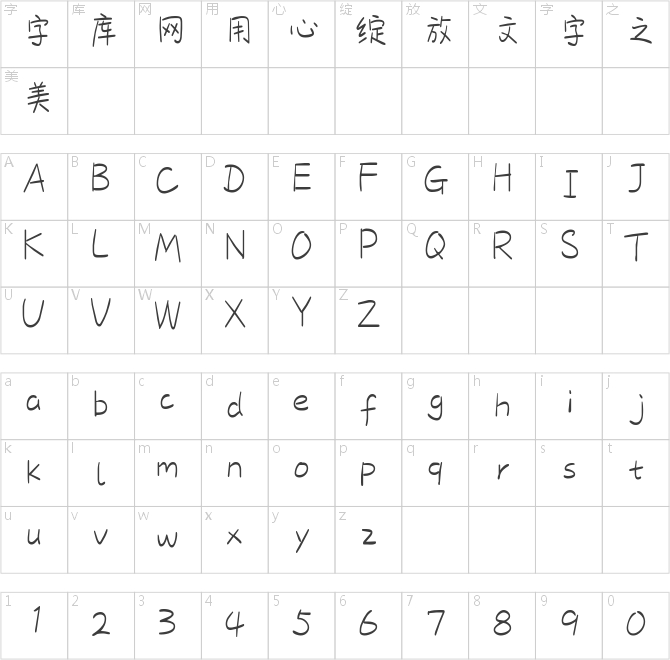
你與溫柔皆可珍藏字體下載文道你與溫柔皆可珍藏
你與溫柔皆可珍藏字體文道你與溫柔皆可珍藏字庫(kù)是一款讓人賞心悅目、百看不厭的中文字體,適合各類(lèi)廣告和產(chǎn)品包裝設(shè)計(jì)應(yīng)用,字體大小4.16MB,格式為ttf字體,上傳用戶(hù)是文道字庫(kù),作者/版權(quán)方為文道字庫(kù)